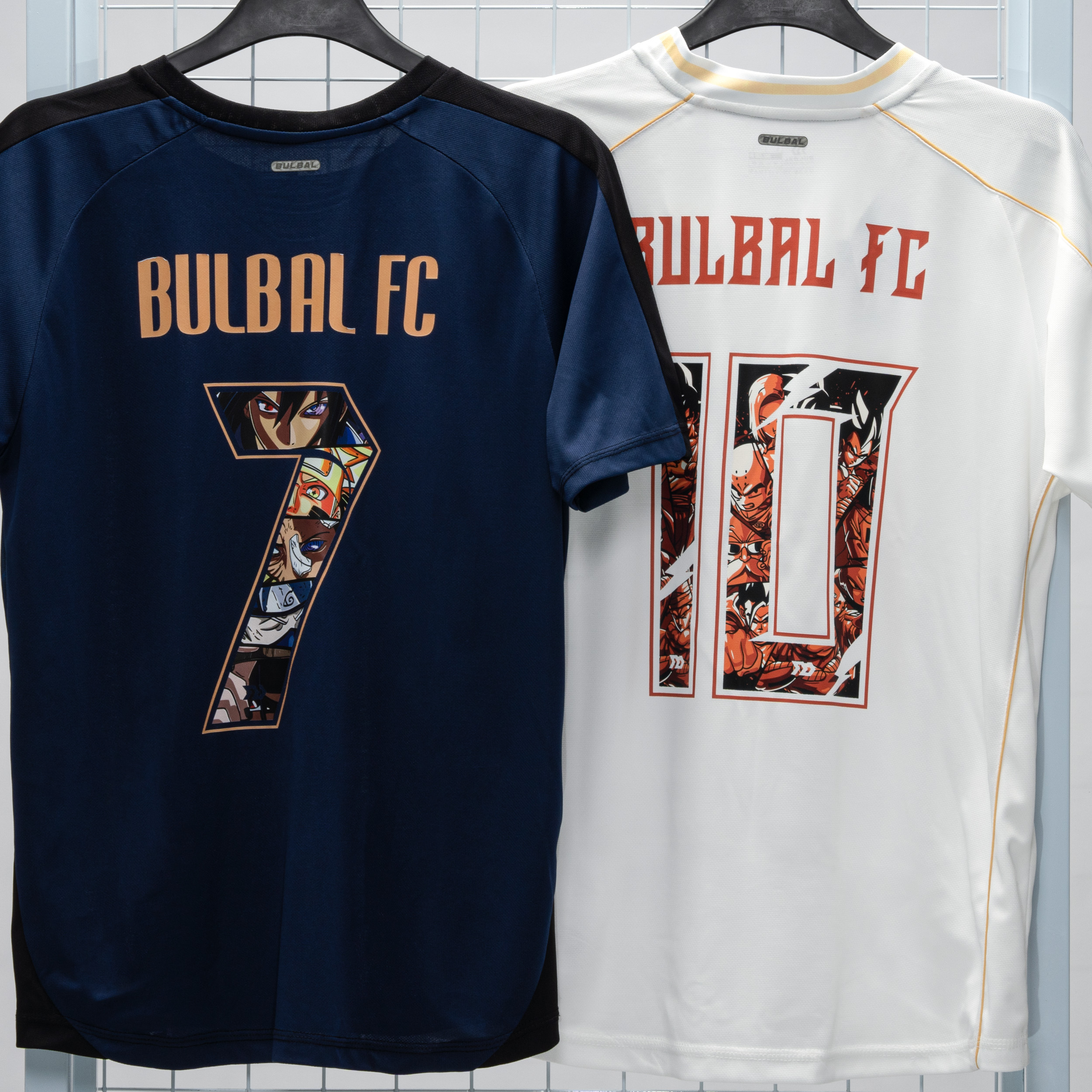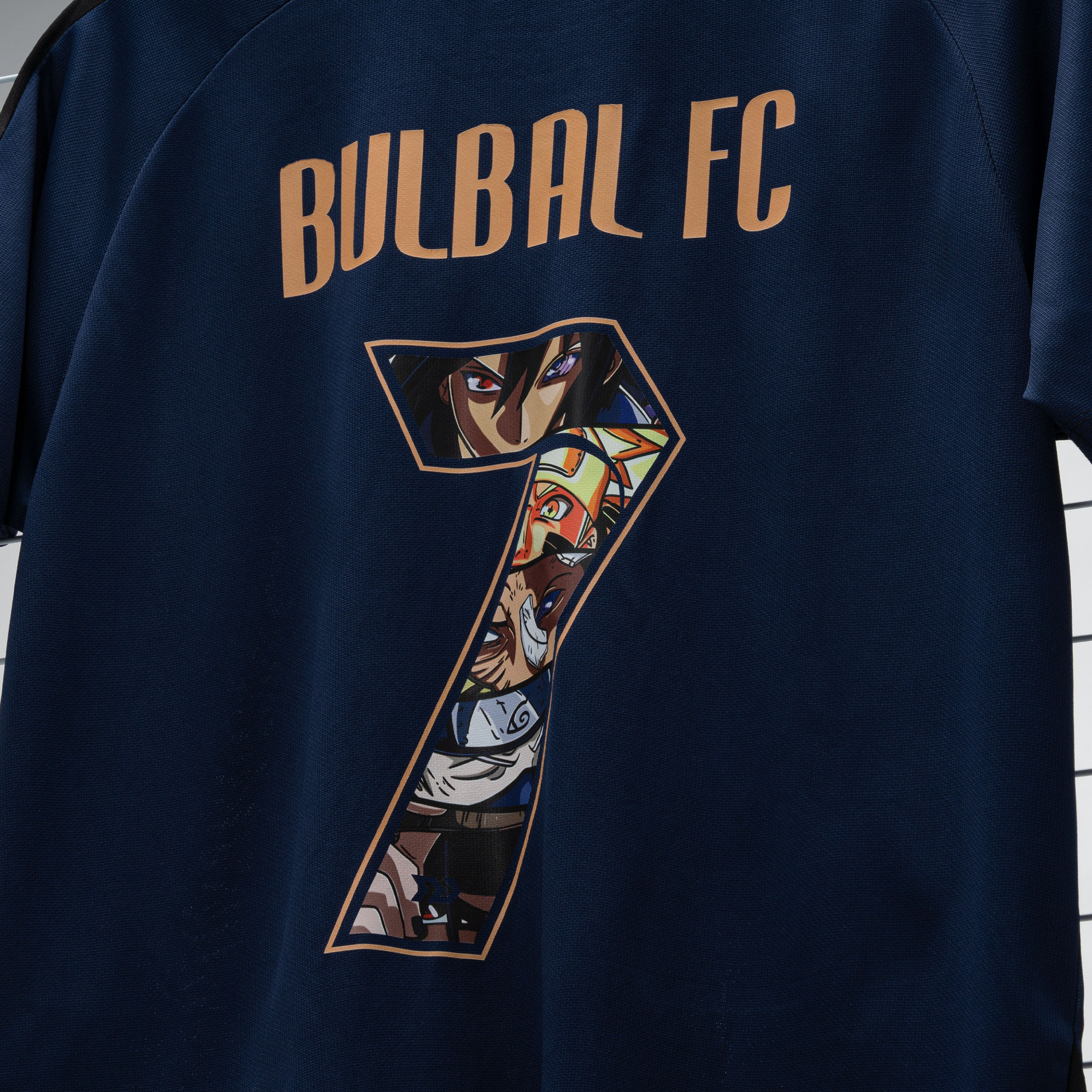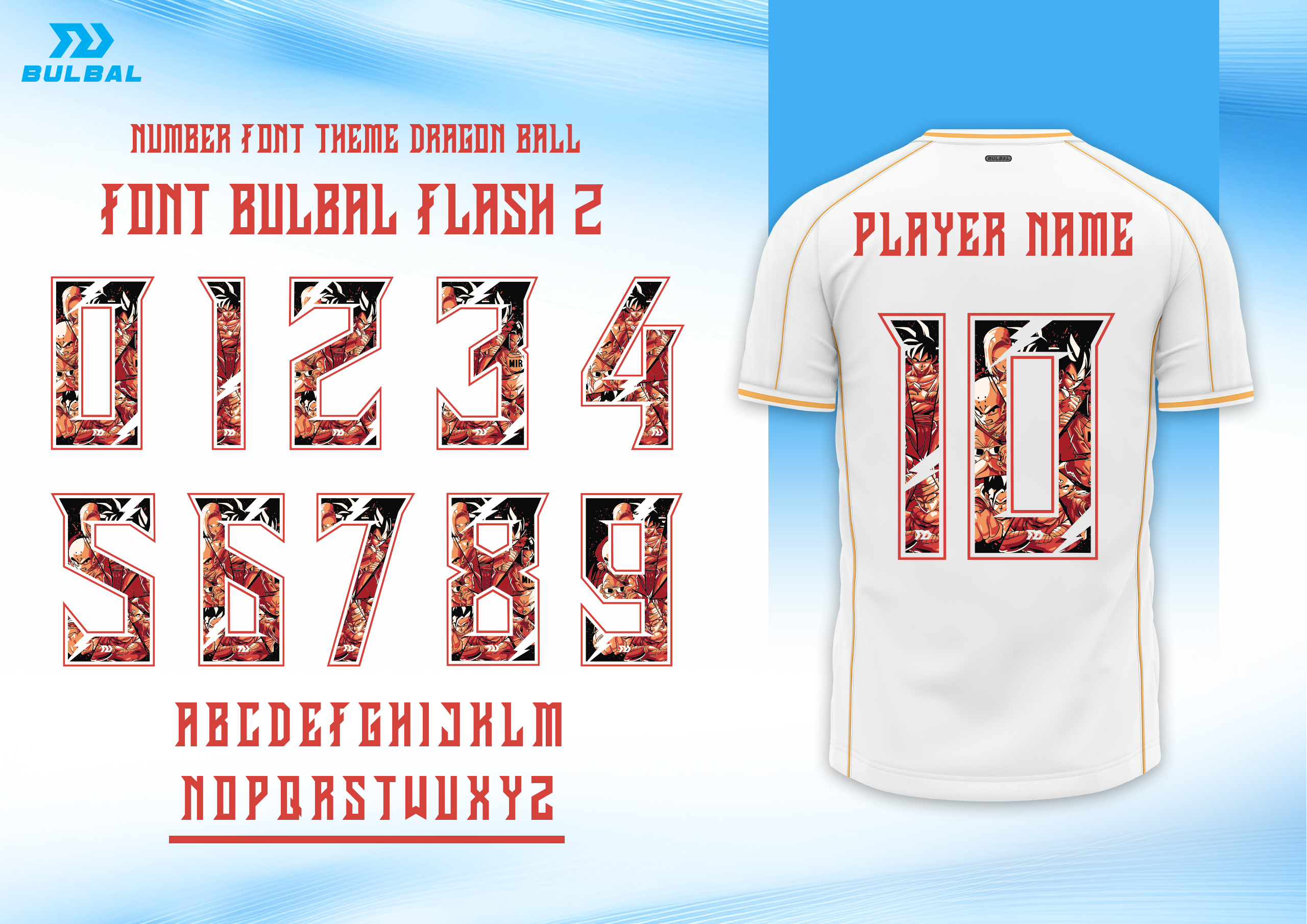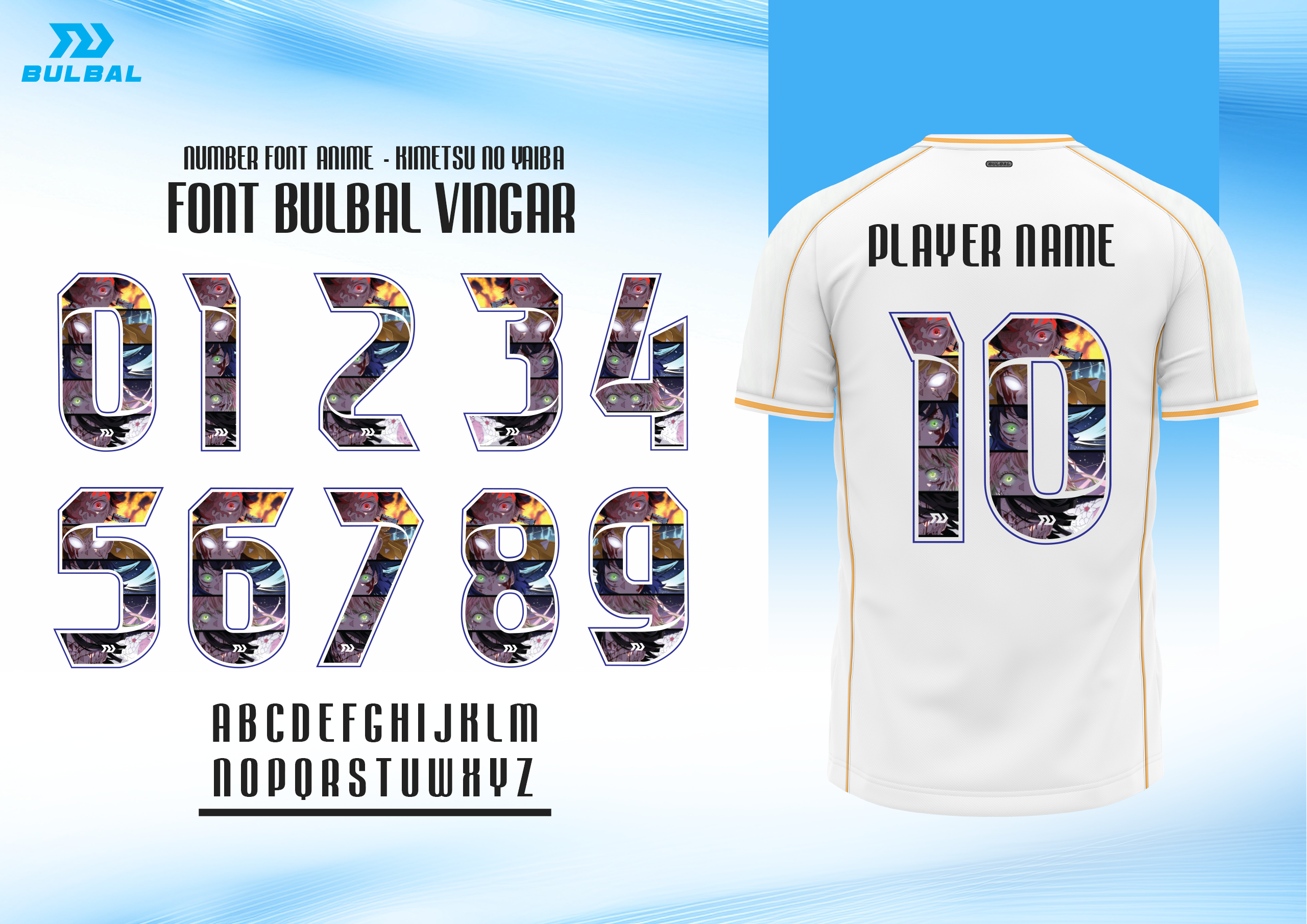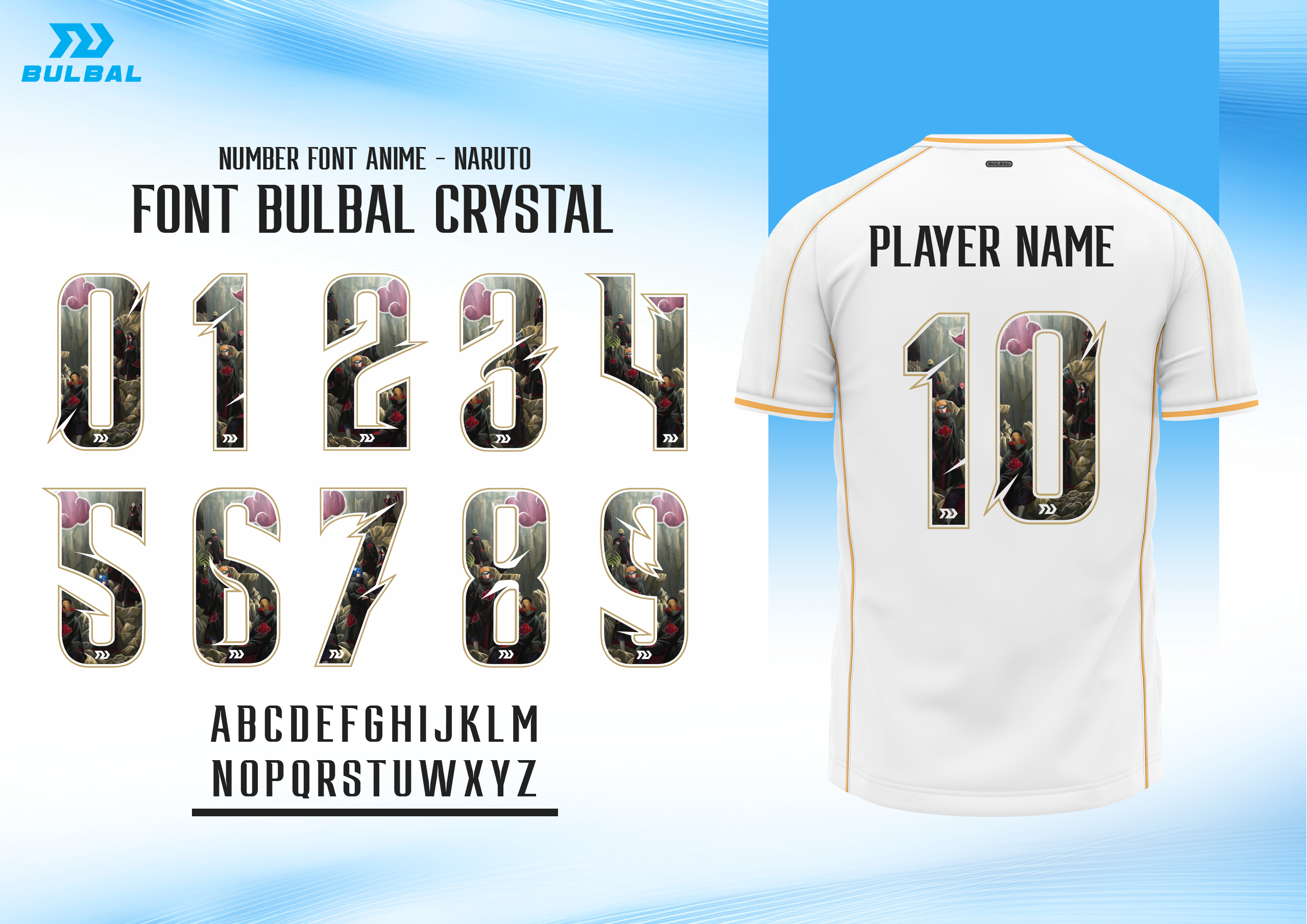
Anime không chỉ là một phong cách nghệ thuật, đó là một nền văn hóa được hàng triệu người yêu mến trên khắp thế giới. Lần đầu tiên tại Việt Nam, Bulbal mang phong cách anime vào thiết kế font số đồng phục đấu bóng, tạo ra sự kết hợp độc lạ đến mỗi chi tiết.
Font số anime của Bulbal được thiết kế dựa trên phong cách nghệ thuật từ những bộ anime nổi tiếng như Naruto, One Piece, Dragon Ball, Attack on Titan, đến những anime fantasy như Demon Slayer, My Hero Academia. Mỗi con số mang dấu ấn của sự mạnh mẽ, huyền ảo, và trực quan đậm chất anime.
Hãy tưởng tượng, khi đội bóng của bạn bước ra sân với những chiếc áo đấu có font số Naruto đậm chất “nhẫn thủ làng lá” hay đường nét của One Piece, gây ấn tượng bằng phong cách phiêu lưu. Font số Dragon Ball mang sự năng lượng sáng tạo và táo bạo, Attack on Titan mang theo khí chất hào hùng. Mỗi chiếc áo đấu sẽ trở thành tuyên ngôn phong cách. Ngoài ra với đa dạng font số đến từ nhà Bulbal, font số Bulbal Anime còn đem lại cho người dùng những ưu điểm vượt trội:
Thiết kế độc đáo, chi tiết tỷ mỹ:
Đường nét font số được cách điệu tảo nên sự chắc chắn và cuốn hút.
Hiệu ứng đồ họa tinh xảo, kết hợp màu sắc độc đáo, tạo điểm nhấn tuyệt đối trên sân cỏ.
Phong cách linh hoạt, tùy biến:
Font số phù hợp với mọi màu áo đấu, từ tào nhã đến sống động.
Phù hợp với cả đội bóng đạm phong cách anime và những người yêu mến nghệ thuật nhật bản.